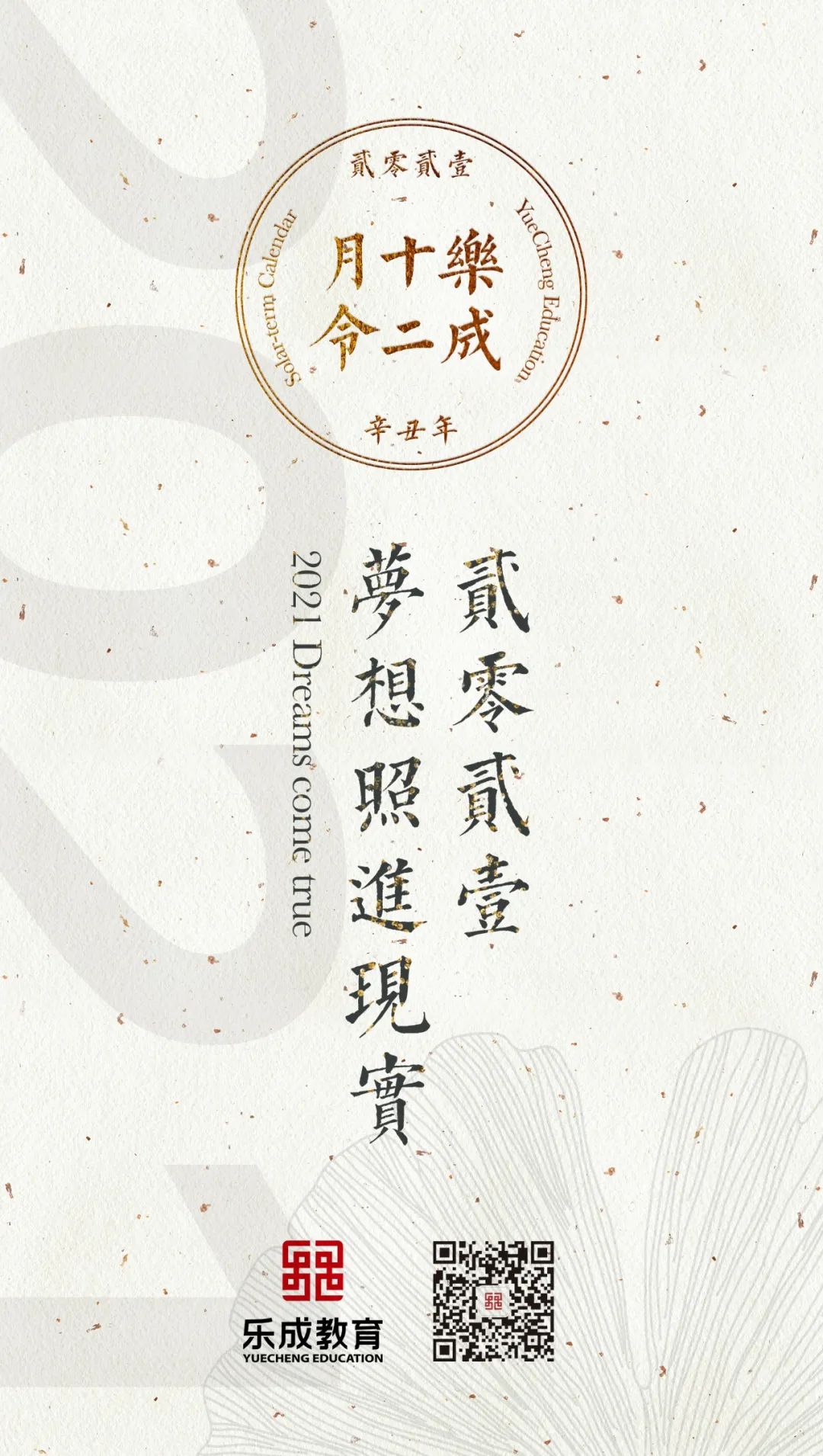
方正国美进道体
中国美术学院汉字设计创新研究所
宋体、仿宋
2021
作为首款高校定制字体,方正国美进道体力求还原国立艺术院(中国美术学院原初机构)原版信笺中瘦细的仿宋体风格,整体上遵循横细竖粗的笔画特点,在造型上再现了聚珍仿宋的刻刀质感与盎然古意,其笔画规范、造型统一,强调版刻、书法、印刷在同一款字体中的平衡与共存,力求打破字库中常见规格化、工业化、模式化的视觉形态,在传承中国美术学院文脉的同时,传递国美的温度。
溯及现代仿宋体创作的源流,尤以钱塘丁氏兄弟(丁三在、丁辅之)新创的聚珍仿宋体最为成功。
聚珍仿宋体因“字体之古雅动人,以之刊行古书,可与宋椠元刊相埒”,一时间成为社会风尚,
凭借极高的可识别性和审美性,在国内引发印刷、美术界开发仿宋体的热潮。
《聚珍仿宋版式各种样张》封面,上海:聚珍仿宋印书局,1923
中国美术学院历来体察时代发展,
受杭州地缘文化的影响,早在新文化运动社会视觉变革时期,就感受到杭州书刻这一脉“字体设计”的力量。
1928年,中国美术学院建校,名曰“国立艺术院”之时,
便使用具有聚珍仿宋风格的仿宋刻版字体作为校方信笺字体。
国立艺术院信笺纸,其刻本字体风格深受聚珍仿宋风潮影响,1928
介绍西洋艺术,整理中国艺术,调和东西艺术,创造时代艺术
信笺上的四句话是中国美术学院初创时的学术主张,
校方将其作为学术旗帜镌刻在信笺之上,引为学院的使命与担当。
在方正国美进道体开发初期的论证会上,中国美术学院校方达成一致意见:
将国立艺术院校方信笺上的字体作为国美首款定制字体的风格源头,
从中寻找设计灵感,以此弘扬和传递新时代的国美精神。
中国美术学院定制字体设计团队从寥寥十六个字的字体模本中寻找视觉共性,
探索既能保留国美文脉,又能适应当下复杂应用场景的字体形态。
经过了反复试验和不同设计方法的尝试,
在历时近一年的调整、修改之后,方正国美进道体终于问世。
作为中国美院的首款高校定制字体,方正字库与国美进行联合设计操演,
希望将南宋临安刻书、浙东文风、欧体欹侧险峻、杭州丁氏聚珍铜活、艺专初建星火等联通一贯;
同时希望将国美的手作精研与方正字库的智能计算较好地结合,
协力将文风书体、科技艺术、自用公传融于一气。
方正国美进道体,其名源自国立艺术院创始人蔡元培为国立艺术院第一、二届毕业纪念刊的题词「技进乎道」。
“技可进乎道,艺可通乎神”之意,方正国美进道体以技入字,
其设计以至刚、至大、至中、至正为最高旨趣,
融刀刻之爽利、自然书写之提按顿挫于一体,追求清朗爽豁、沉雄奇崛的境界。
方正国美进道体力求还原国立艺术院原版信笺中瘦细的仿宋体风格,
整体上遵循横细竖粗的笔画特点,在造型上再现了聚珍仿宋的刻刀质感与盎然古意,
其笔画规范、造型统一,给人以赏心悦目之感。
欧阳询的书法风格对后世影响极大,其结体长方、笔画方正、书风端正;笔画整齐尖锐,容易以雕刻表现。
《淳化祕阁法帖考证十二卷》,刻于扬州广陵般若庵的《冬心先生集》,均是清代欧体仿宋字的代表刻本
方正国美进道体从欧楷的章法中汲取神采妙道,
通过字形大小、长短、伸缩、开合、运笔节奏及笔力气势的变化,将字体组合成一个平衡统一的整体。
方正国美进道体借鉴欧体楷书的章法与笔势,笔画部件流露出书写的意趣与韵律
方正国美进道体取欧体之结体手法,中宫紧密,重心上提,凝神聚气,贯注如虹。
中宫紧密,重心上提
其余笔画分领纵展,以字中为核心,余笔外拓。
方正国美进道体所呈现的优美灵动的笔调,与书法中的神情意趣妙相契合,
从而使静止的字形,变得神采飞扬,生机勃勃。
余笔外拓,笔势舒张
方正国美进道体贯彻楷书据情相让的部件特点,“发于左者应于右,起于上者伏于下”,
整体大小以右让左,以上让下,形成左宽右窄、下宽上窄的疏密对比。
左大右小,字距疏朗
上窄下宽,皆相逊让
顺应书法手写的笔势,方正国美进道体横画朝右上倾斜,左右部件之间形成高矮向背,
其形势递相映带、四方照应,如此便有盎然生趣。
横向左低右高,笔势向右呈开扇状
方正国美进道体多个笔画之间相互呼应,笔画之外的空白部分均匀协调,气韵贯通,视觉上舒适得当。
布白均匀、气韵贯通
为了调整笔画间的顺应性与空间分布,保证笔画粗细视觉上的均等,
方正国美进道体依照不同字符内横画、竖画笔数的不同,
而对横竖笔画的粗细进行了更细节化的演绎和设定。
根据笔画数量调整笔画间的顺应性与空间分布
方正国美进道体将欧体楷书的章法之美、神采气质、书意韵律,贯注于点画之中,
在端正稳健的视觉风格基础上,做到上下俯仰、内紧外松、笔意顾盼,参差有致、富于变化,
既融合了书法字体与印刷字体的特征,也融合了字体美学的观赏性与实用性,
在追求再现刻本仿宋古意盎然风格的同时,又能够符合现代排版印刷需求的设计理念。
中国美术学院以一贯的先锋意识,整体观览全球境域与本土情境,
坚持中西融合和传统出新两条学术脉络,融汇中西、匠心独造、铸练艺术。
方正国美进道体的配套外文、符号设计,则将这种“中西协调、各守传统”的主旨融于字体的血脉之中。
笔形一致,各守传统
大小写字高差异大,字距合理、灰度一致
方正国美进道体的拉丁字符大写高度约为汉字高度的80%,
拉丁字母及数字的字干粗细大致比汉字的少笔画字粗10%,
在中英混排中,西文、数字的灰度基本与汉字保持一致而略微醒目,
符合一般混排时的阅读需求。
中西文混排时保证视觉协调,符合阅读需求
字体设计师在创作过程中,融合国美一贯抱持的美学理念,为智能赋予情感与艺术修养。
字体融入国美温度,打破了参数化的疏离感,同时注重字体功能性的诉求——精致疏朗、严谨易读,
以适应字形的多场景应用需求。
由方正字库与中国美术学院携手呈现的方正国美进道体,
获得了GDC Award 2021专业组优异奖
以及纽约TDC 2022 Certificate of Typographic Excellence(字体优秀奖)
同时字体入选2022东京TDC 年鉴